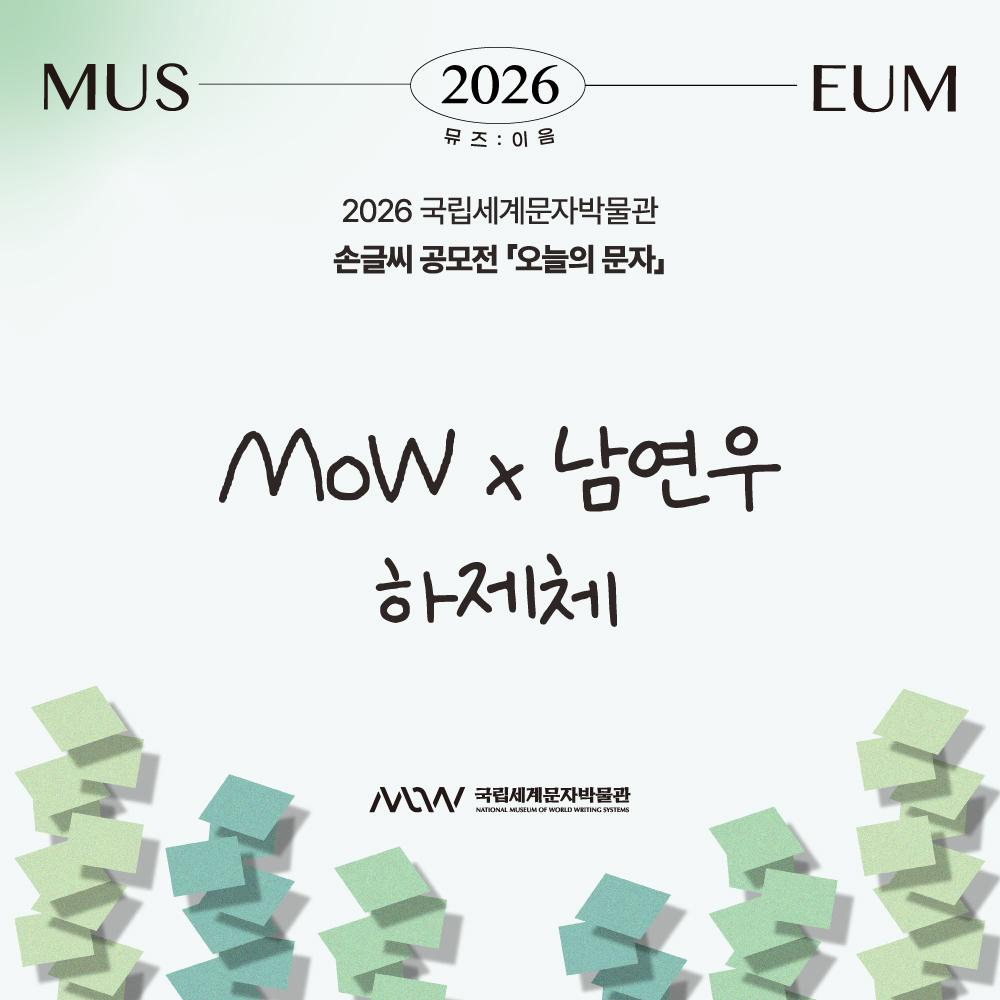
그리운 하제체
Griun Haje Font
그리운 하제체 소개
2026 국립세계문자박물관 손글씨 공모전 <오늘의 문자> 이 폰트는 2026 국립세계문자박물관 손글씨 공모전 <오늘의 문자> 수상자의 손글씨를 바탕으로 제작되었습니다. 수상자의 정갈하고 따뜻한 손글씨의 특징을 디지털 폰트에 담아, 손글씨만의 자연스러운 개성과 손으로 글씨를 쓰는 감성을 디지털 환경에서도 이어갈 수 있도록 구현했습니다.